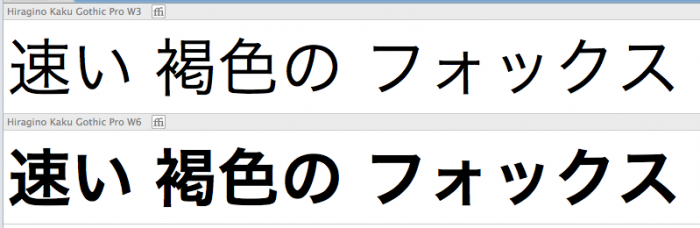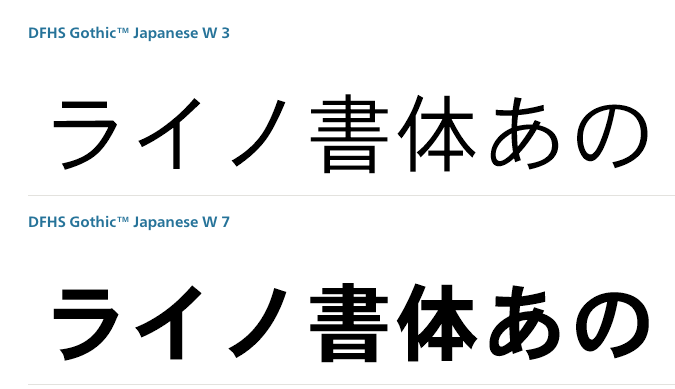
Welcher japanischen Font kommt der DFHS Gothic am nächsten?
Ich suche einen kostenfreien japanischen Font, der der DFHS Gothic sehr nahe kommt:
Hab ich eventuell einen durchs Mac OS schon installiert und weiß es nur nicht?
Versuche mal die Hiragino Kaku Gothic Pro. Konnte gerade zwar in der Glyphentabelle deine Buchstaben nicht finden (welch Wunder), aber ich finde, die Anmutung geht in die gleiche Richtung.
Der liegt auch in zwei Schnitten vor, genau das, was ich brauch  :biglove: